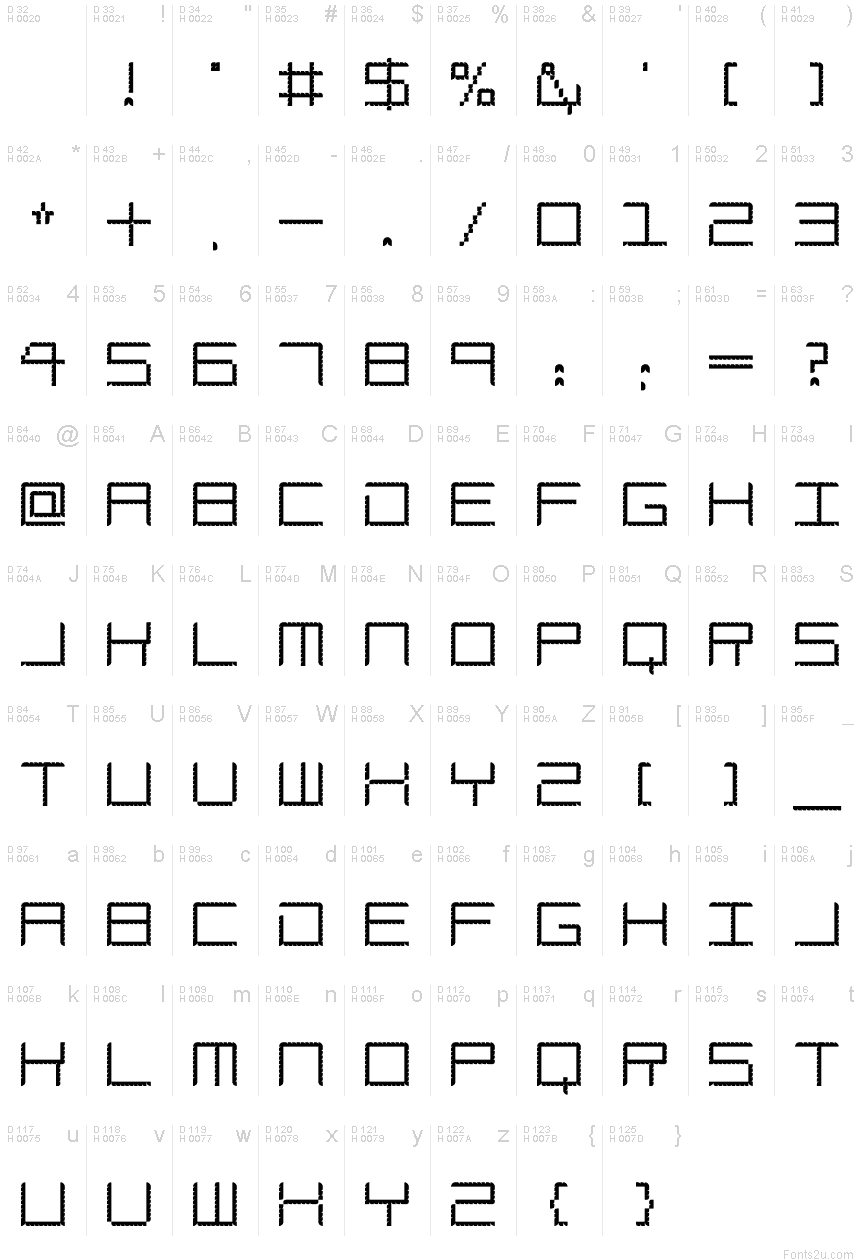
Amaya Technical Curve, eine kostenlose Techno-Display-Schrift von Snapdragongirl, verwandelt abgerundete, quadratische Buchstabenformen in ein Design, das irgendwo zwischen Schaltplan und Stickmuster liegt. Die Großbuchstaben setzen sich aus breiten, gleichmäßigen Strichen mit abgesetzten Ecken und einem wiederkehrenden, sägeblattartigen Rand zusammen – das Ergebnis wirkt mechanisch, aber dank der verspielten Note keineswegs streng.
Diese Mischung eignet sich hervorragend für Gaming-Logos, Sci-Fi-Flyer, Musik-Cover, Titelkarten und Interface-Design, bei denen ein kostenloser Font für eine starke, synthetische Stimmung sorgen soll, ohne kalt zu wirken. Er funktioniert auch gut für kurze Überschriften und Monogramme, da der gezackte Rhythmus selbst einfachen Wörtern eine gemusterte, emblemartige Präsenz verleiht.